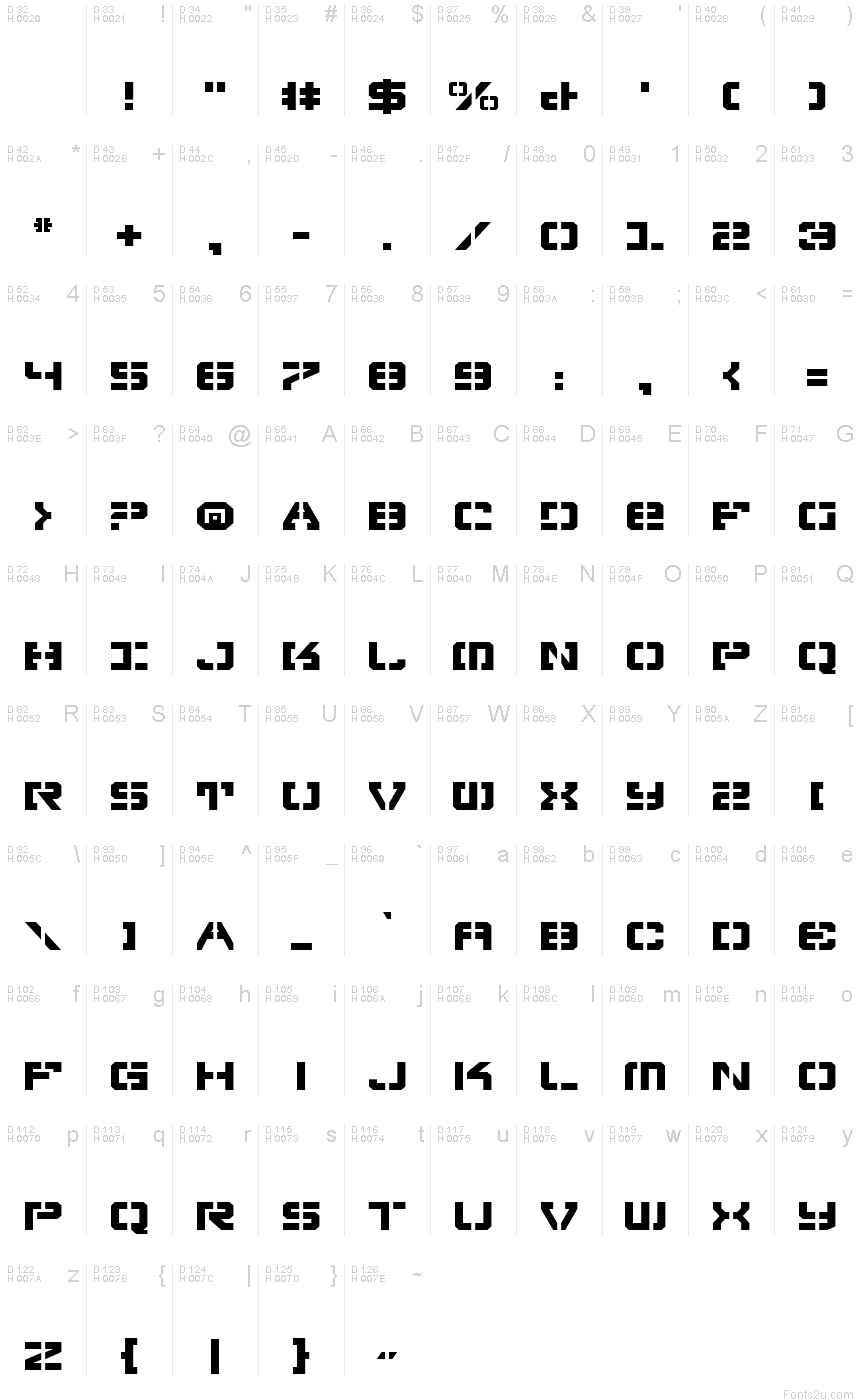
Vyper Expanded by Iconian Fonts to darmowy, futurystyczny krój pism typu display, zbudowany z szerokich, kanciastych form. Ostre narożniki i prostokątne wycięcia nadają literom maszynowy profil.
Motywy technologiczne i science-fiction sprawiają, że krój ten idealnie nadaje się do grafiki gier, plakatów wydarzeń oraz okładek muzyki elektronicznej. Napisy mogą stać się częścią samej kompozycji wizualnej, przypominając raczej wyświetlacz panelu sterowania lub emblemat przemysłowy niż zwykły tekst.
Vyper Expanded